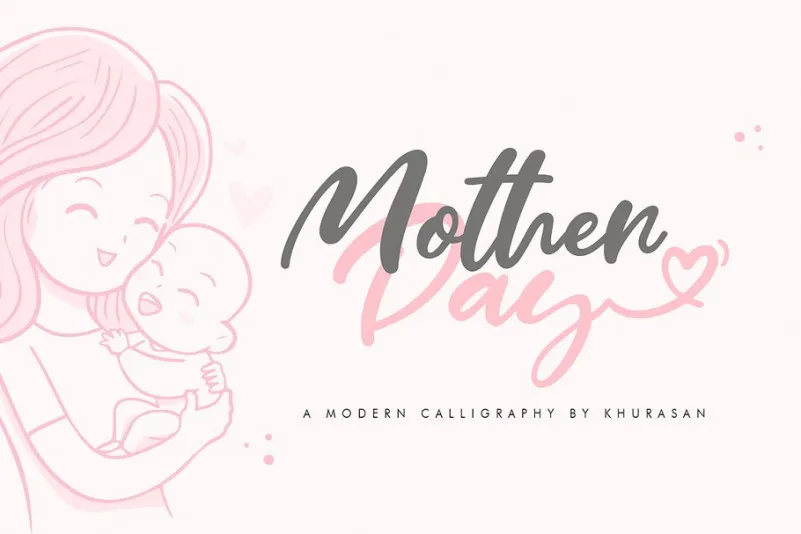
Mother Day Script Font – Download Grátis
Esta é uma tipografia moderna inspirada na caligrafia, adequada para criações digitais com estilos elegantes e sofisticados. Introduzimos a fonte “Mother Day”, criada pelo designer khurasan. Esta tipografia de script tem um design leve e fluido, oferecendo uma aparência feminina, sensual e glamorosa. A fonte é simples mas encantadora, perfeitamente adequada para projetos informais como cartões de alegria ou até mesmo produções formais, como convites, selos, menus de restaurante, logomarcas, embalagens, revistas, livros e cartas de casamento. Ela atinge o coração do seu projeto com facilidade, proporcionando uma aparição elegante e sofisticada que se adapta a diversos ambientes. Não importa onde você decida aplicar essa fonte, ela certamente será um recurso visual fascinante para qualquer tipo de produção criativa.